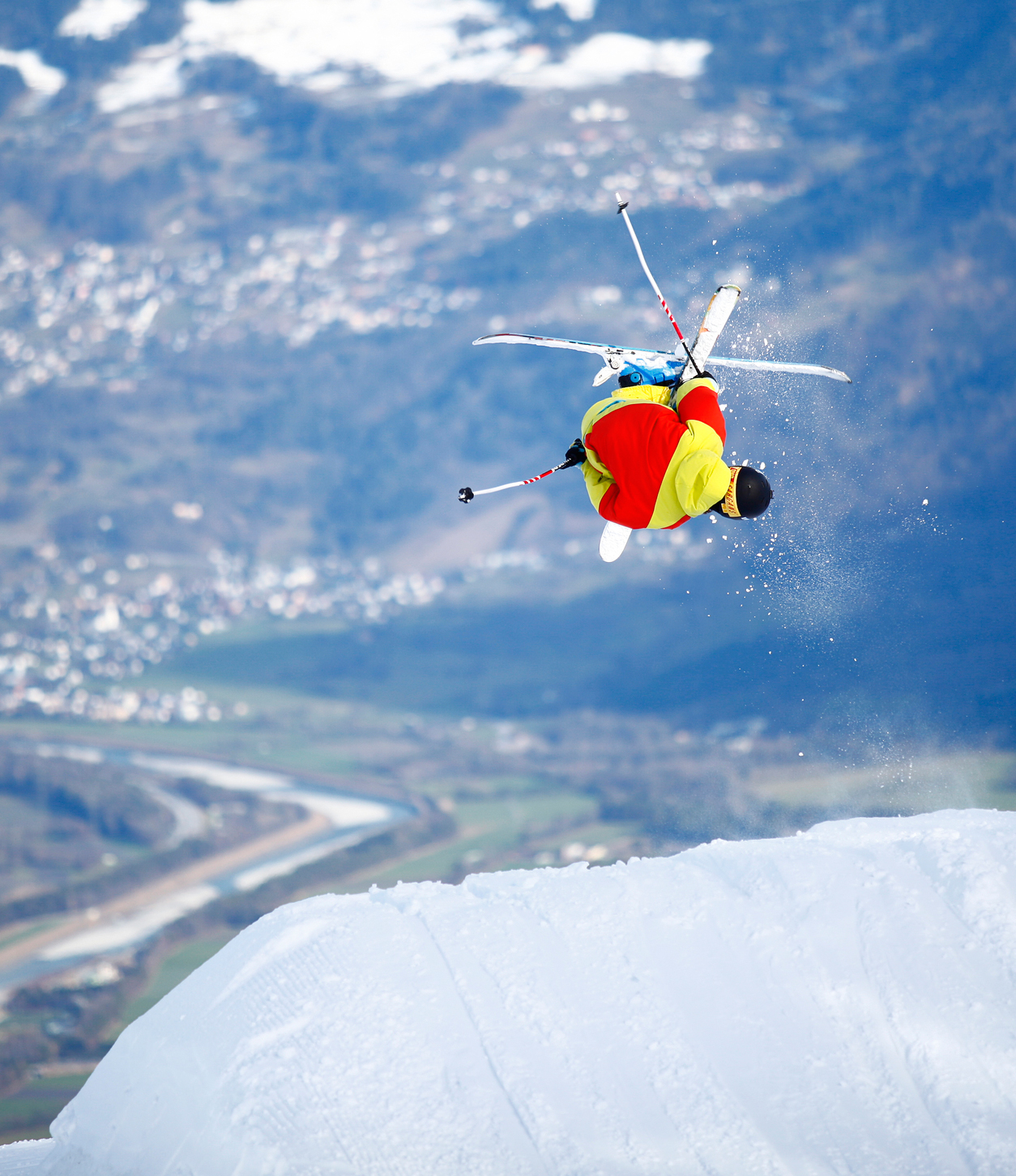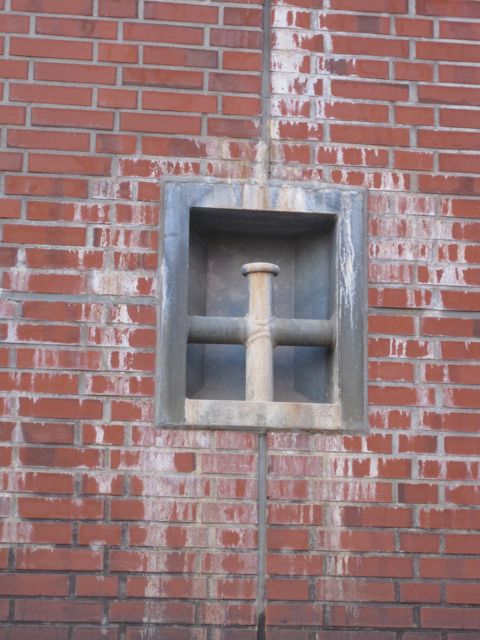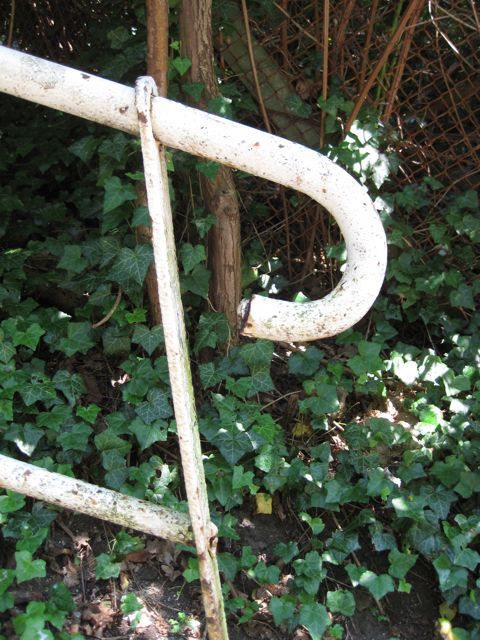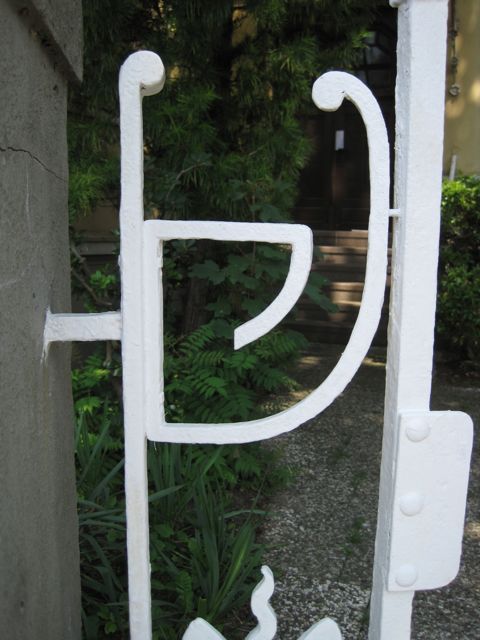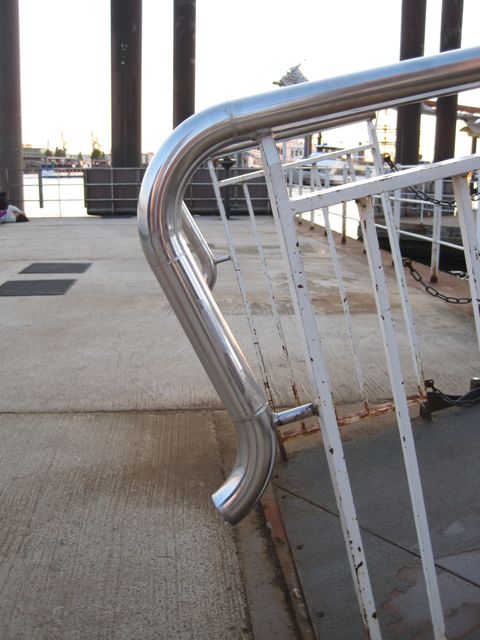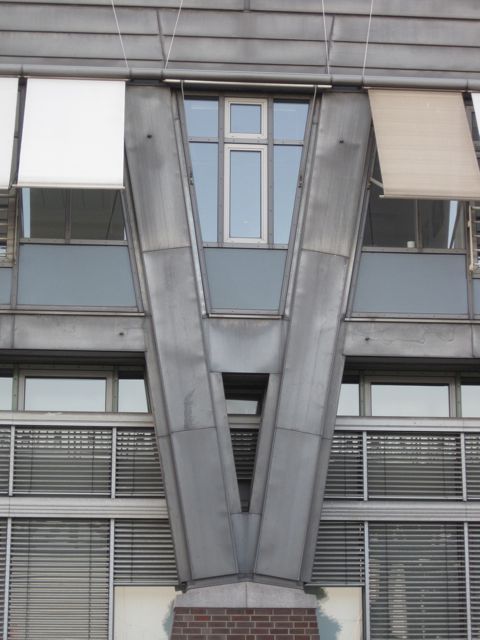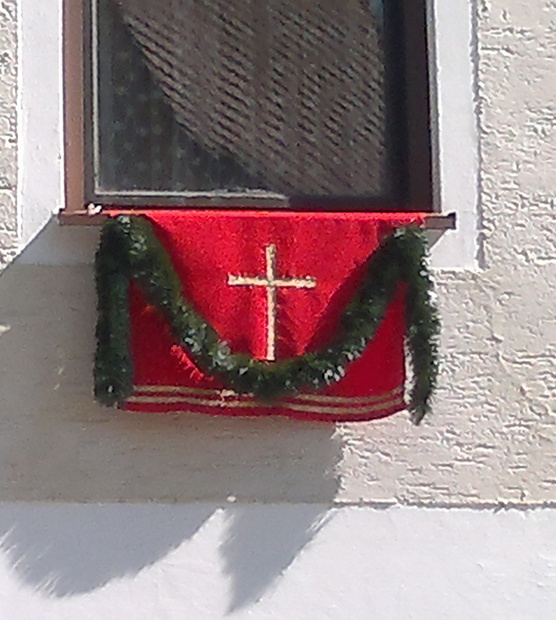
Buchstaben entdecken
Zu Erntedank typografisch dekoriertes Dorf
… etwas verdichteter betrachtet sind in deiner Fahnengirlanden-Schrift zusätzlich zwei «Ligaturen» implokludiert: «ut» und «mt». Wozu auch immer …
Mein Söhnchen mit sowas wie einem Freestyle-Asterisk (Dezember 2012).
Soho, ich war mal wieder mit der Typophiliertrommel unterwegs … :huhu:
Das wurde allerdings auch höchste Zeit, ich musste schon das Moos von diesem Thread entfernen, bevor ich die Tür überhaupt wieder aufbekam …. Dafür habe ich aber sogar ein @ und einen Doppelpunkt gefunden und im zweiten Teil gibt es ein + und ein Komma – oder eine 9, je nach Lesart.
Das hing bei uns an der FH im Seminarraum unserer Typo-Professeuse  :nicken:
… und bei meinen Kindern im Kinderzimmer :schonklar: . Meine Frau hat es vor Jahren aus dem Fundus gegraben und den Kurzen hat es gefallen :biglove: